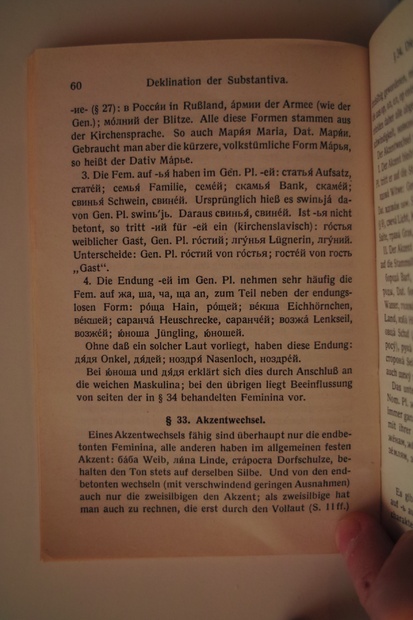
römisch - romanisch - irgendwas
eure antworten letztens hatten mich auf die idee gebracht, meine russisch bücher zu durchsuchen.
(da bei der literaturnaya dabei stand sie hätte sich aus der lateinischen von berthold entwickelt)
und siehe da in der angefügten russischen grammatik von 1961 (sammlung göschen band 66) / druck thormann & goetsch
findet sich beinahe exakt dieselbe schriftart die ich suche.. sie scheint nur etwas gestaucht und die porportionen beim W (aufgrund der kleineren gesamthöhe?) mußten wohl leicht angepaßt werden...
aber die schrift is ansonsten exakt dieselbe... vor allem die charakteristische unterlängen beim J, K, und R, oder das überbreite H, etc.
die romana t book enthält zwar dieselben kleinbuchstaben, es fehlen aber gerade diese charakteristischen großbuchstaben..
die literaturnaya enthält zwar die großbuchstaben mit unterlänge, jedoch reicht beim großen M die mittellinie nicht! bis an die grundlinie heran und passt auch sonst nicht wirklich...
(vor allem wie kann ich gezielt nach kyrillischen fonts suchen? die lateinische von berthold kann ich auch schonmal nicht finden.. mir fehlt ein bißchen die vorkenntnis um hier kompetenter weiterzukommen)
Die Literaturnaya sollte es eigentlich bei allen gängigen Schriftanbietern im Web geben. Am sichersten ist aber wohl Paratype, da gibt es sie auch in verschiedenen Belegungen.
Was die Unterschiede zur digitalisierten Variante der Literaturnaya betrifft, so könnte es sich hier um unterschiedliche Entwurfsgrößen handeln, die sich jeweils auch optisch geringfügig unterscheiden. (Falls es denn die Literaturnaya ist.)
es handelt sich hierbei ja eben NICHT um die literaturnaya... die großbuchstaben wie K und R entsprechen zwar ganz gut der gesuchten schrift, aber das markante unterlängen J in der gesuchten schrift hat in der literaturnaya gleich überhaupt keine unterlänge. ansonsten würde ich mir, keine ahnung ob das so 1-2-3 geht, in einem fonteditor aus den 2 schriften(literaturnaya und romana t book) eine einzelne zusammenstellen...
gibt es eine digitale version der lateinischen von berthold?
Based on Latinskaya of the H. Berthold (St.Petersburg, 1901), Cyrillic version of Lateinisch of H.Berthold (Berlin, 1899).
Verstehe ich richtig, daß Du genau die Schrift aus diesem Buch verwenden möchtest? Warum genügt nicht eine ähnliche? Genau diese Schrift wird es digital wohl nicht geben. Obwohl diese Lateinisch/Römisch-Schriften früher weit verbreitet waren, gibt es nur wenige Digitalisierungen. Im Thema »Römische Antiqua« habe ich die mir bekannten digitalen Schriften genannt: Literaturnaya, Quant (in zwei verschiedenen Fassungen) und Romana. Bertholds Lateinisch gibt es meines Wissens leider nicht digital. Die Quant dürfte noch die beste für Lesegrößen geeignete digital verfügbare Schrift dieser Art sein.
ansonsten würde ich mir, keine ahnung ob das so 1-2-3 geht, in einem fonteditor aus den 2 schriften(literaturnaya und romana t book) eine einzelne zusammenstellen...
Das geht nicht so einfach und ist auch Unsinn, weil die beiden Schriften völlig unterschiedliche Strichstärken haben, die Buchstaben also nicht zusammenpassen; außerdem ist es wahrscheinlich nicht erlaubt.
du bringst es auf den punkt.... es muss eine dem charakter der schrift entsprechende sein...
sprich annähernd die gleiche. deine alternativen scheiden somit aus.. der eindruck den man beim lesen hat ist einfach nicht derselbe..... (die proportionen passen nicht)
friedrich kraus' opus magnum erfordert nunmal exakt diese schrift... da sie von sehr unterschiedlichen personen, die den inhalt zu verdauen imstande waren, als sehr stimmig empfunden wurde. obendrein ist es keine 'exotische' brotschrift zwischen 1750-1850.
das schriftbild des sperrsatzes wird wahrscheinlich ebenfalls unter den engeren großbuchstaben leiden... das behaupte ich mal in totaler unkenntnis eures handwerkes...
@schriften mischen im fonteditor...
die strichstärken sind natürlich ein argument... die einwände von wegen nicht dürfen sind vollkommen lächerlich.
(am endergebnis ist ja nicht ersichtlich WIE ich zu dem ergebnis gekommen bin.....)
Sehe ich absolut nicht so. Wenn man ein wie von Dir beschrieben erzieltes Schriftergebnis in einem Fonteditor öffnen und die Positionen der Ankerpunkte mit den Vorlagen der zusammenkopierten Schriften vergleichen würde, dann wäre sicherlich im Nu bewiesen, aus welchen Quellen Du Dich bedient hast.
Ja, das würde mich auch interessieren.
Ach Kathrinvdm!
bist du vielleicht herzig... ich hab selten so gelacht.